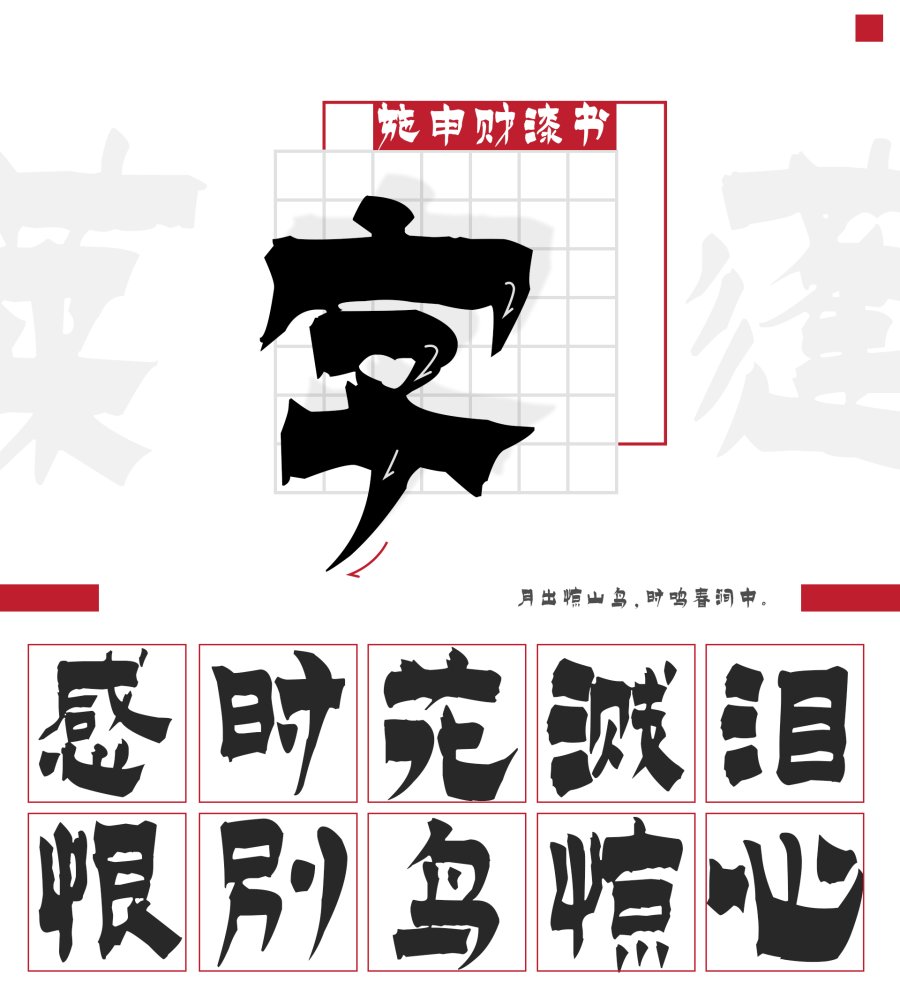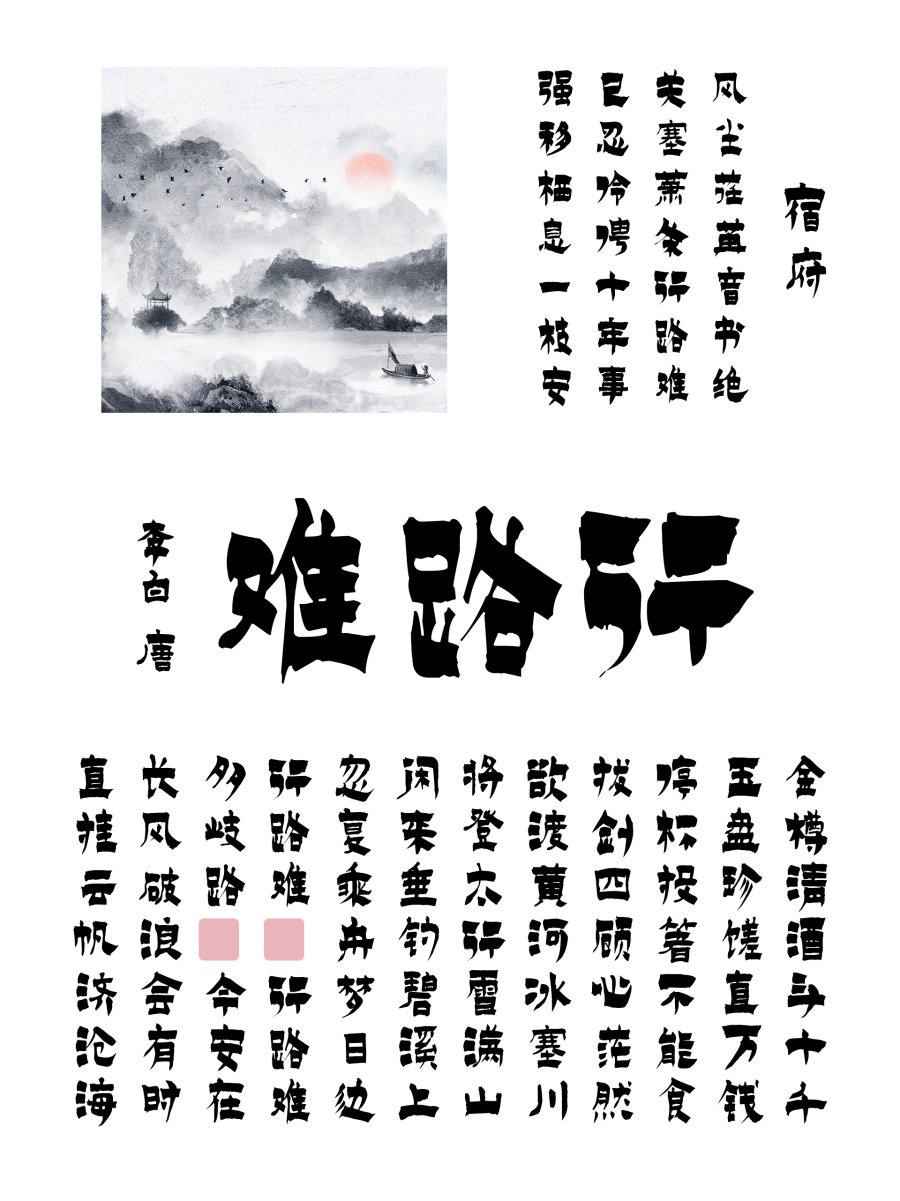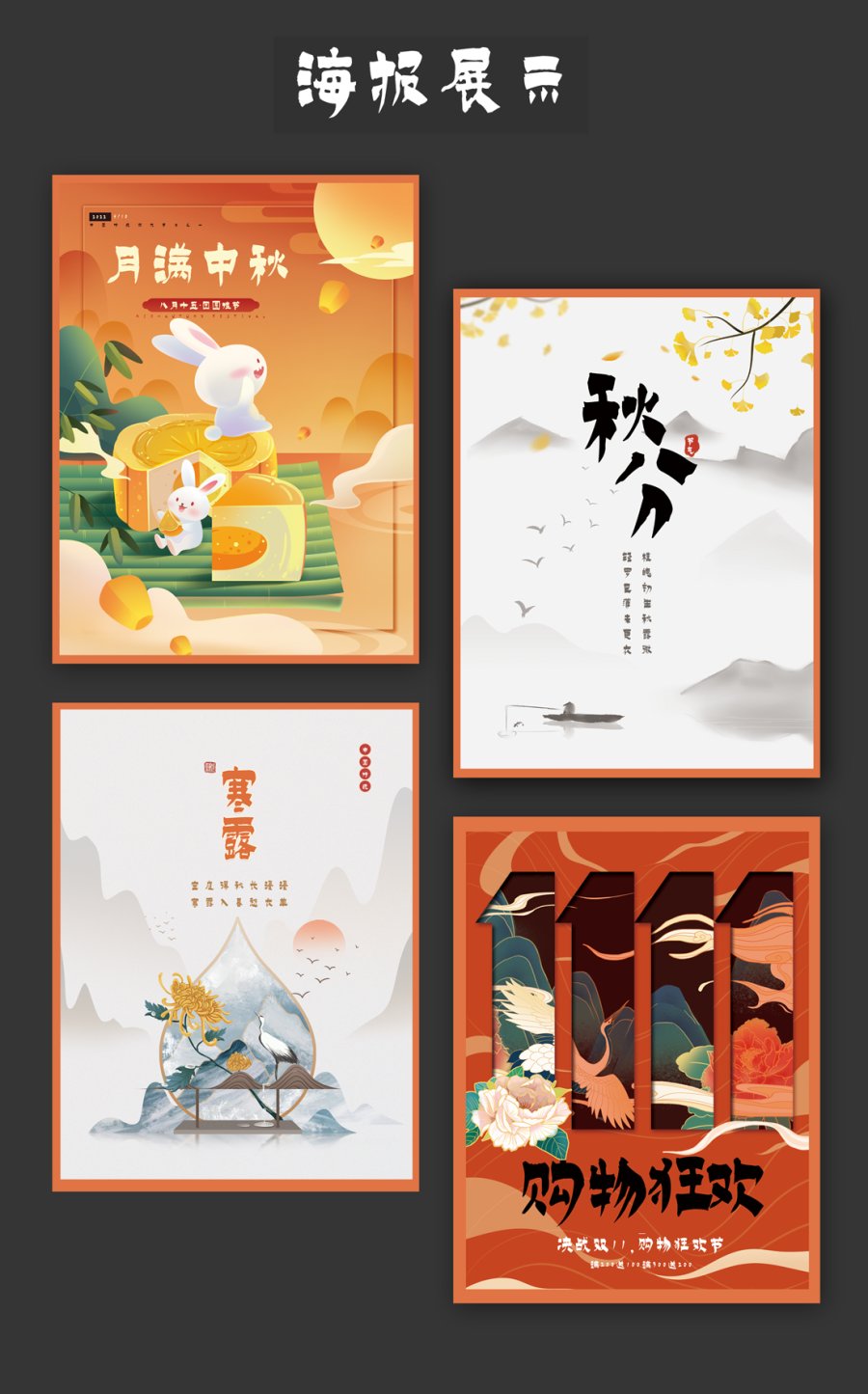
集楷、隶于一体的变体书法-施申财漆书
施申财漆书体
施申财漆书
该字体定位为漆书,其实是楷、隶于一体的变体书法。以北魏楷书笔意书之,间夹隶书,字体方正,字态静穆古拙,看似字字断开,而其间笔意顾盼映带,整套字体给人以一种古朴生拙的气息。
施申财漆书
外形粗壮豪迈、外刚内柔,突出表现了中国书法线条美与力量美,对于喜欢以书法字体为标题的设计师们而言,这款字体美感也是不言而喻的。
施申财漆书
该字体不仅可以用作GOLO标志,还可以应用在各种海报标志设计方面。
施申财漆书